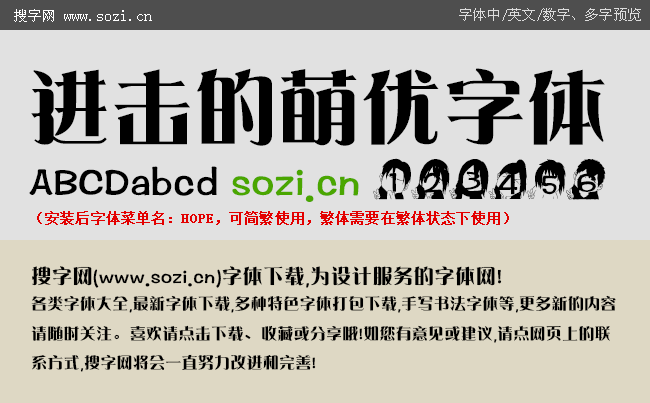
进击的萌优字体
搜字网给大家提供一款艺术风格的手机中文字体下载。字体名字叫进击的萌优字体,这款手机字体是以华康雅宋体字体为原形。数字部分加上了漂亮的卡通外框,华康雅宋体以宋体的基础上加以美化,比划处修以花边,转折处稍微圆润,相比棱角分明的宋体,又多了一分可亲近的感觉。该字体端正大方,且结构清晰、风格统一,特别适合喜欢手机字体个性一些的朋友在手机上安装使用。